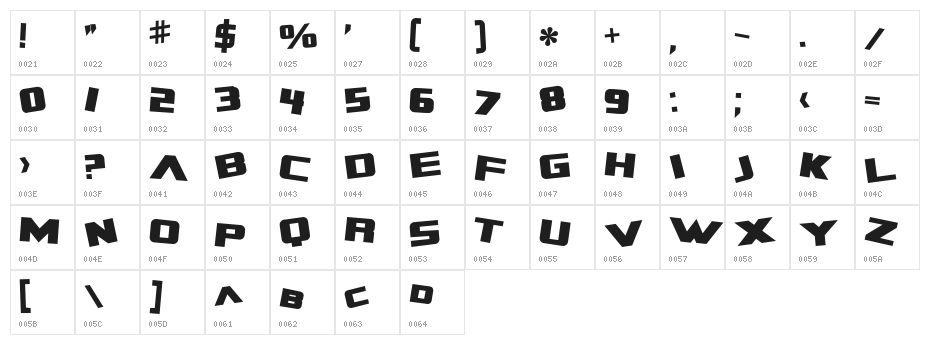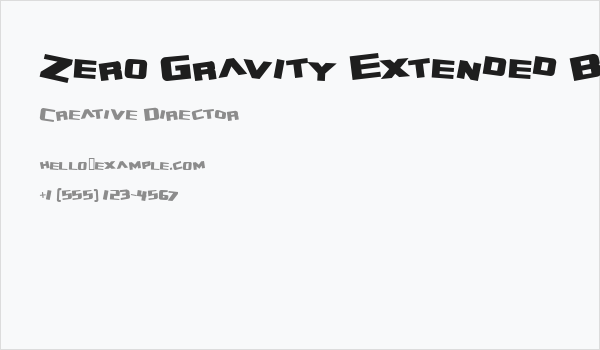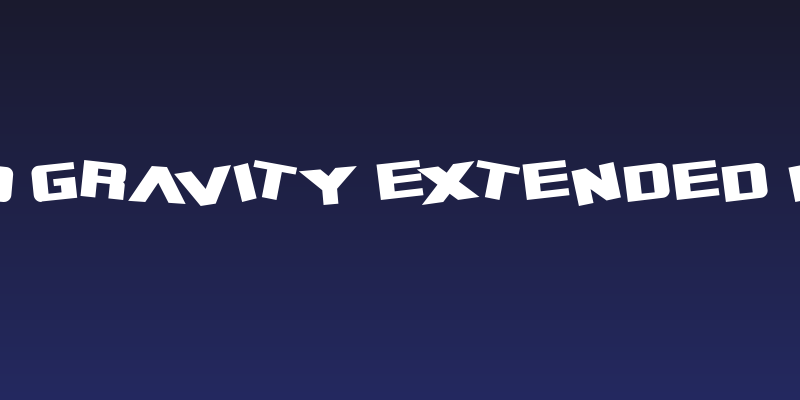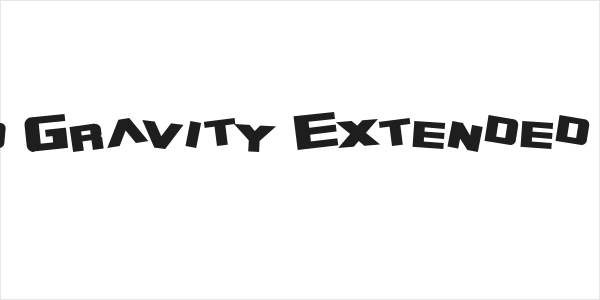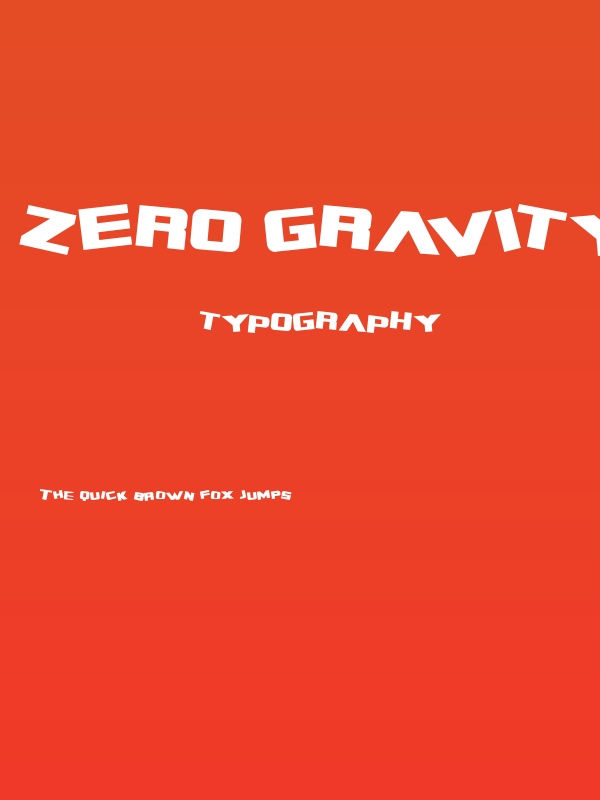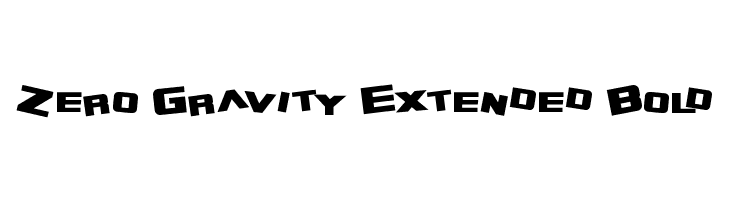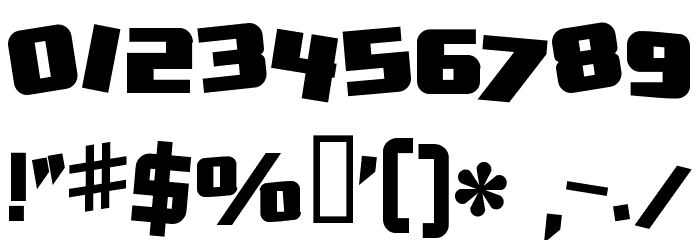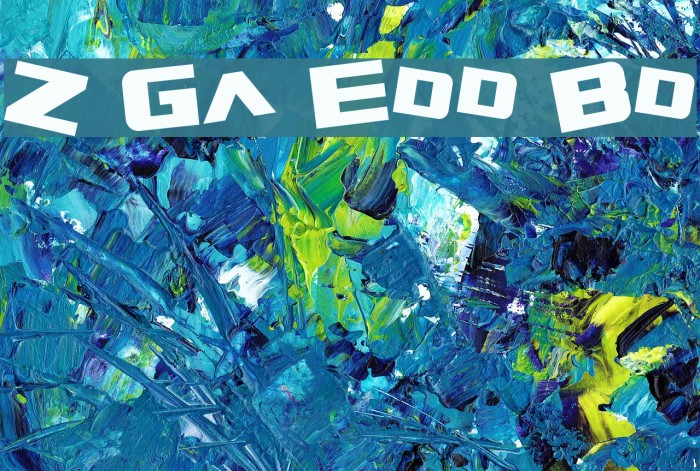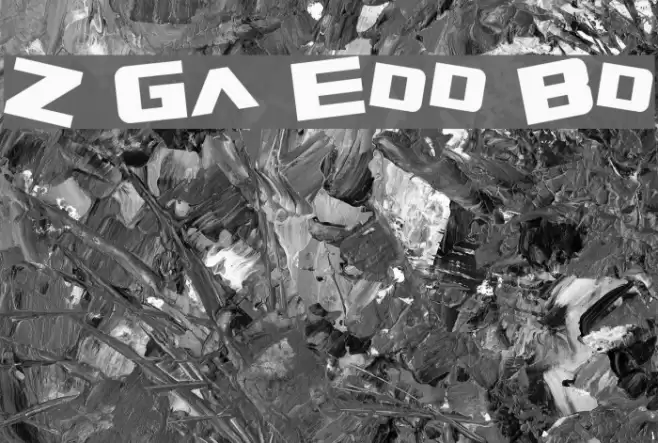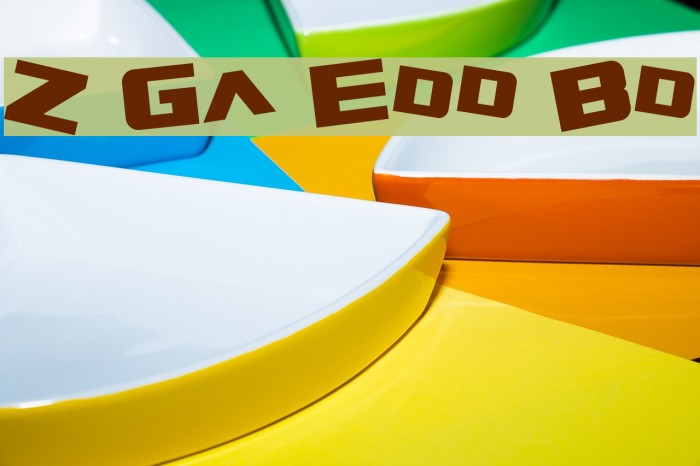
Zero Gravity Extended Bold Font
✎ Capitals
| 名前 | Zero Gravity Extended Bold |
| ウェイト | Bold |
| カテゴリ | Capitals |
| 幅 | Expanded |
| おすすめプロジェクト | Ideal for sci-fi themed posters, video game titles, futuristic branding, and dynamic advertising campaigns. |